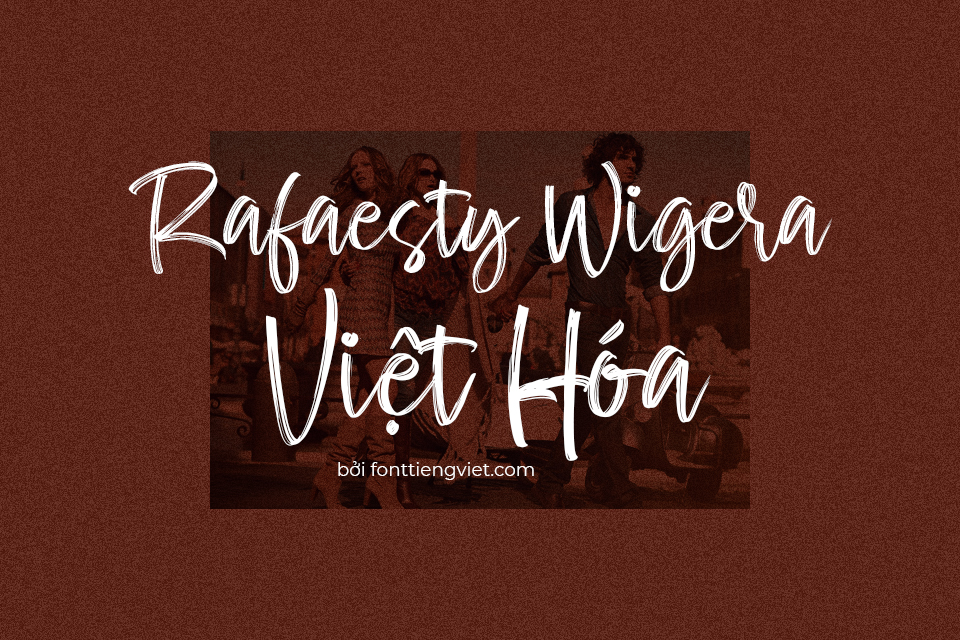
Font việt hóa 1FTV Rafaesty Wigera kiểu brush
Giới thiệu về Font việt hóa 1FTV Rafaesty Wigera kiểu brush
Trong thế giới đồ họa hiện đại, việc tìm kiếm một bộ Font Miễn Phí có phong cách độc đáo luôn là ưu tiên hàng đầu của các nhà thiết kế. Font việt hóa 1FTV Rafaesty Wigera kiểu brush là một tác phẩm nghệ thuật chữ viết tay đầy cá tính, mang đậm dấu ấn hội họa. Với những đường nét phóng khoáng và mạnh mẽ, bộ font này mô phỏng hoàn hảo kỹ thuật vẽ cọ khô, tạo nên sự chân thực và sống động cho mọi bản thiết kế. Phiên bản việt hóa giúp người dùng tại Việt Nam dễ dàng ứng dụng vào các dự án truyền thông mà không lo lỗi font hay thiếu dấu tiếng Việt.
Đặc điểm nổi bật của font chữ kiểu brush
Phong cách phóng khoáng và nghệ thuật
Đặc trưng lớn nhất của Font việt hóa 1FTV Rafaesty Wigera kiểu brush chính là sự tự nhiên trong từng nét chữ. Các nét thanh đậm xen kẽ cùng hiệu ứng xước nhẹ tạo cảm giác như được vẽ trực tiếp bằng cọ trên nền giấy nhám. Điều này giúp bộ font trở nên cực kỳ phù hợp cho các thiết kế cần sự phá cách như bìa sách, poster phim, hoặc áo thun thời trang.